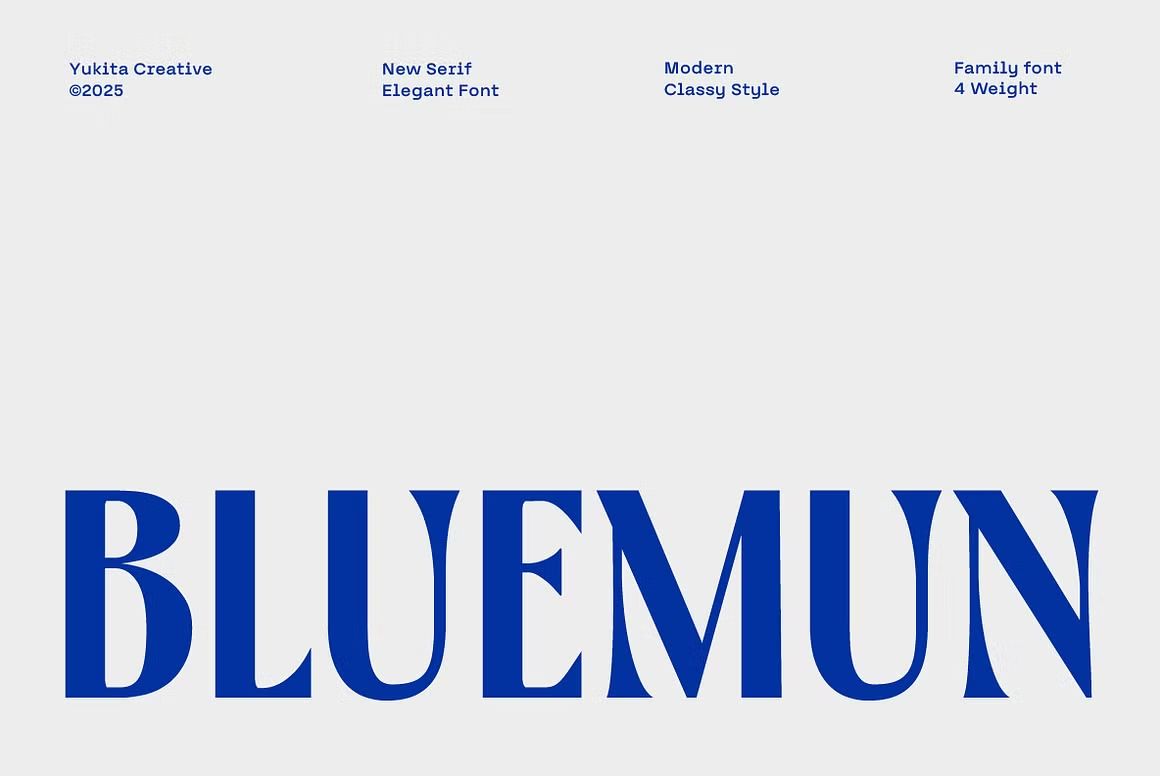
Bluemun – Sans Serif Font
Bluemun adalah font sans serif modern dan minimalis, cocok untuk branding dan desain profesional. Format OTF/TTF/WOFF, siap digunakan di berbagai platform desain.
Bluemun adalah font sans serif bergaya modern dan bersih, dengan bentuk huruf yang simpel namun elegan. Didesain untuk fleksibilitas tinggi, font ini cocok digunakan dalam berbagai proyek desain seperti branding, kemasan produk, editorial, web design, hingga presentasi profesional. Karakternya yang seimbang menjadikan Bluemun ideal untuk tampilan minimalis yang tetap berkelas.
• Gaya sans serif modern dan bersih
• Cocok untuk branding, editorial, dan desain digital
• Termasuk huruf besar, kecil, angka, dan simbol